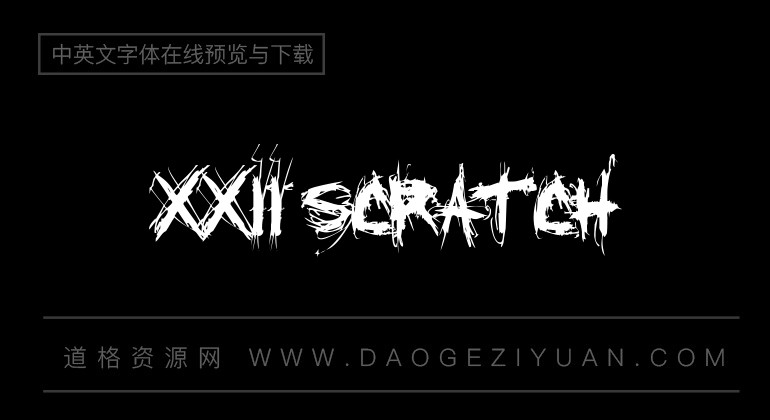
XXII Scratch
XXII Scratch 是一款粗体技术字体,由 Alexey Frolov 创作,由 Typetype 发行。它采用了一种独特的设计,将技术细节与流行的外观结合在一起。它的字体采用了强烈的线条,曲线和细节,使其具有独特的外观和感觉。它的字体也有许多可定制的选项,可以让用户根据自己的需求来调整字体的外观。XXII Scratch 字体可以用于创建多种不同的文档,包括网页、广告、报纸等,使它们看起来更加有吸引力。
XXII Scratch是一款非常不错的手写艺术字体,具有很好的视觉感,适合于文化类的宣传设计、商业类品牌的广告和产品包装设计以及个性化文字排版等较多场景。